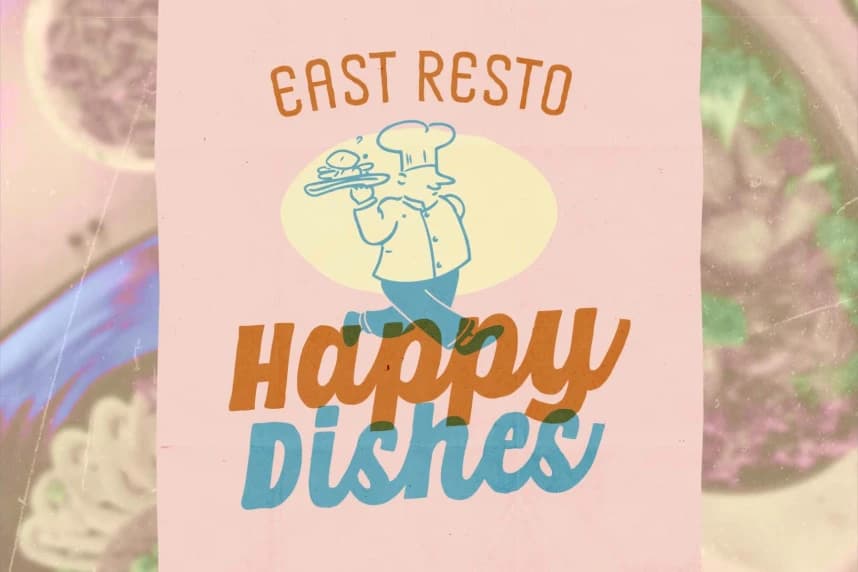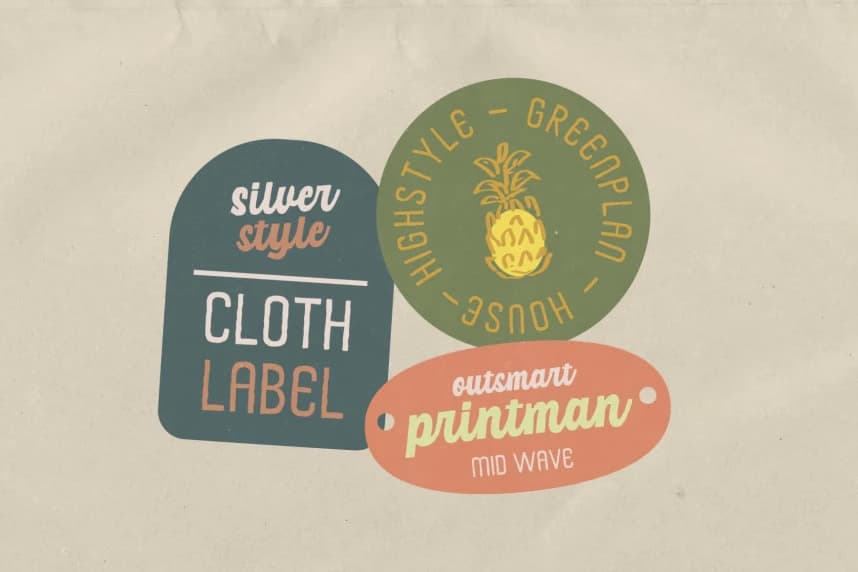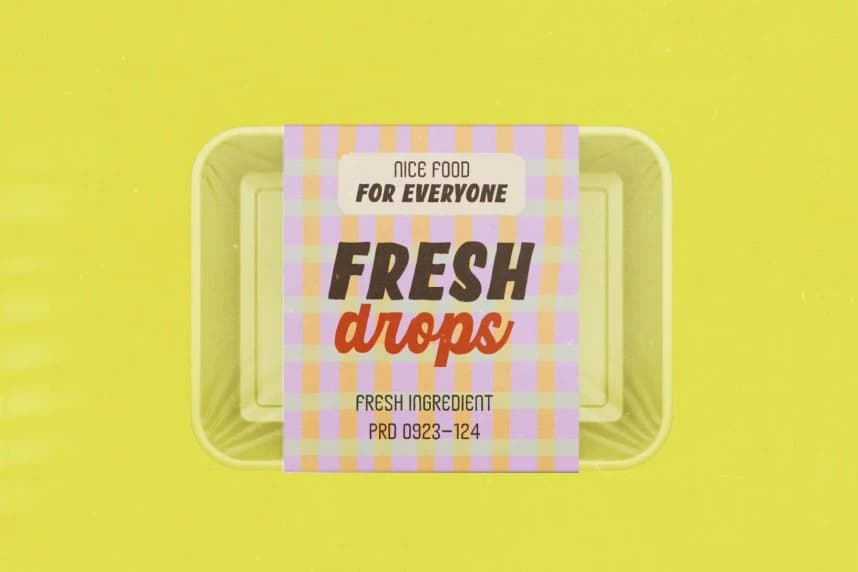
Picsue Yazı Tipi İkili
Picsue Font Duo, el yazısı stilinde tasarlanmış bir gösterim script fontunu dar kesimli sans serif ile birleştiren kalın bir font ikilisi olup, vintage ve retro tasarım temasına uygun iyi ve benzersiz bir kombinasyon sunmak üzere tasarlanmıştır. Kalın yazı stili özgüven veren bir görünüm sağlar.
Picsue Font Duo, kalın bir font ikilisi olup el yazısı stilinde bir gösterim yazı tipi ile daraltılmış sans serif'i bir araya getirir ve vintage ve retro bir tasarım temasına iyi ve benzersiz bir kombinasyon sunmak üzere tasarlanmıştır. Kalın yazı stili güven verir.
Picsue Font Duo